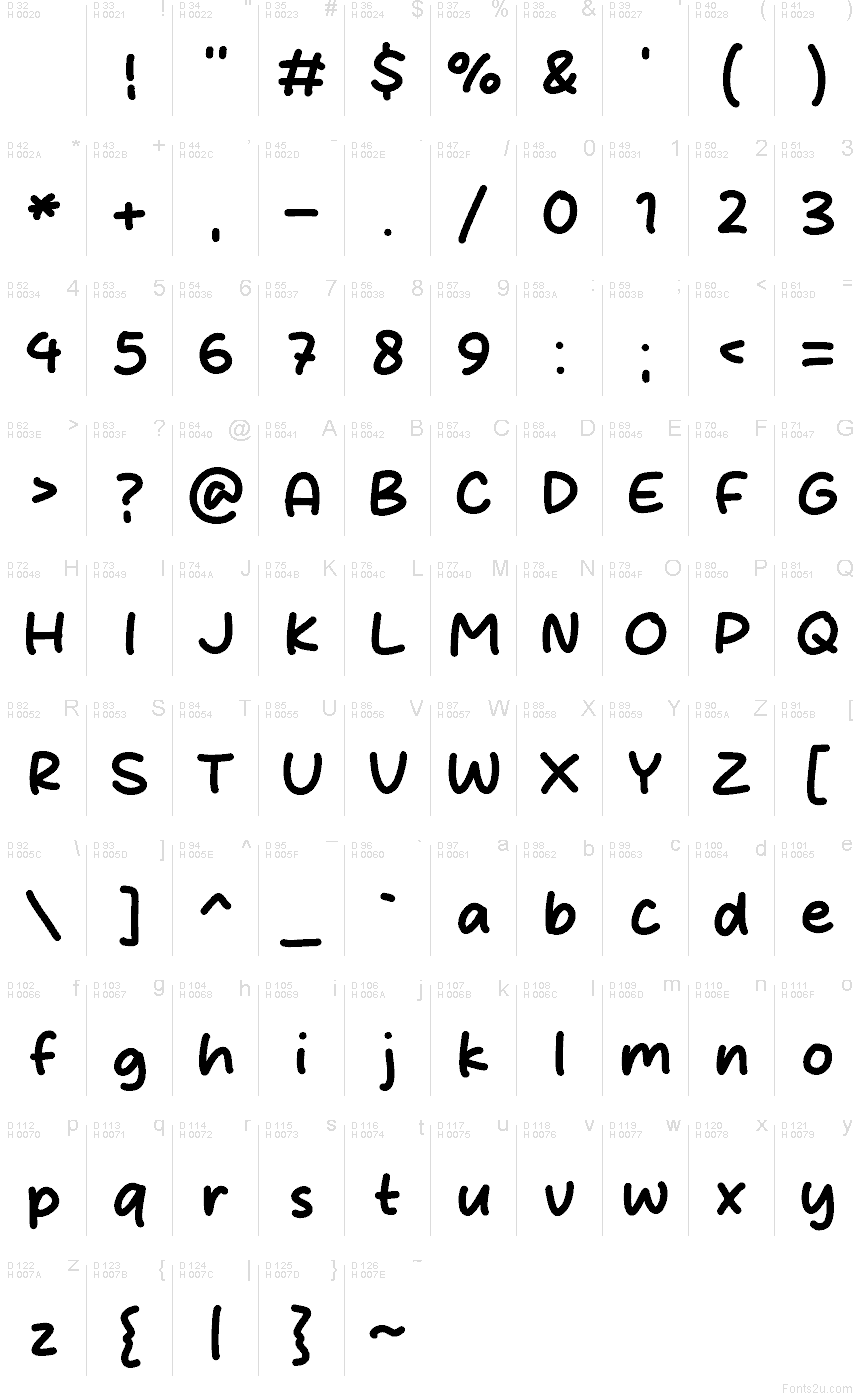
Brown Cookies, par Brown Cookies © (Origin Type), est une police manuscrite gratuite, dotée d'un rebond doux et arrondi ainsi que d'une touche artisanale décontractée. Les lettres apparaissent épaisses et fraîchement dessinées, avec des courbes généreuses, des jonctions courtes et un rythme légèrement irrégulier qui lui donne un aspect décontracté plutôt que mignon.
Elle s'intègre naturellement dans l'image de marque de boulangeries, les menus de cafés, les emballages de snacks, les couvertures de livres pour enfants et les publications joyeuses sur les réseaux sociaux, où une police gratuite doit paraître amicale sans devenir trop sucrée. Utilisez-la pour des titres courts, des croquis de logos, des cartes de titre ou des étiquettes simples : les traits larges et gonflés donnent suffisamment de chaleur et de présence à quelques mots.